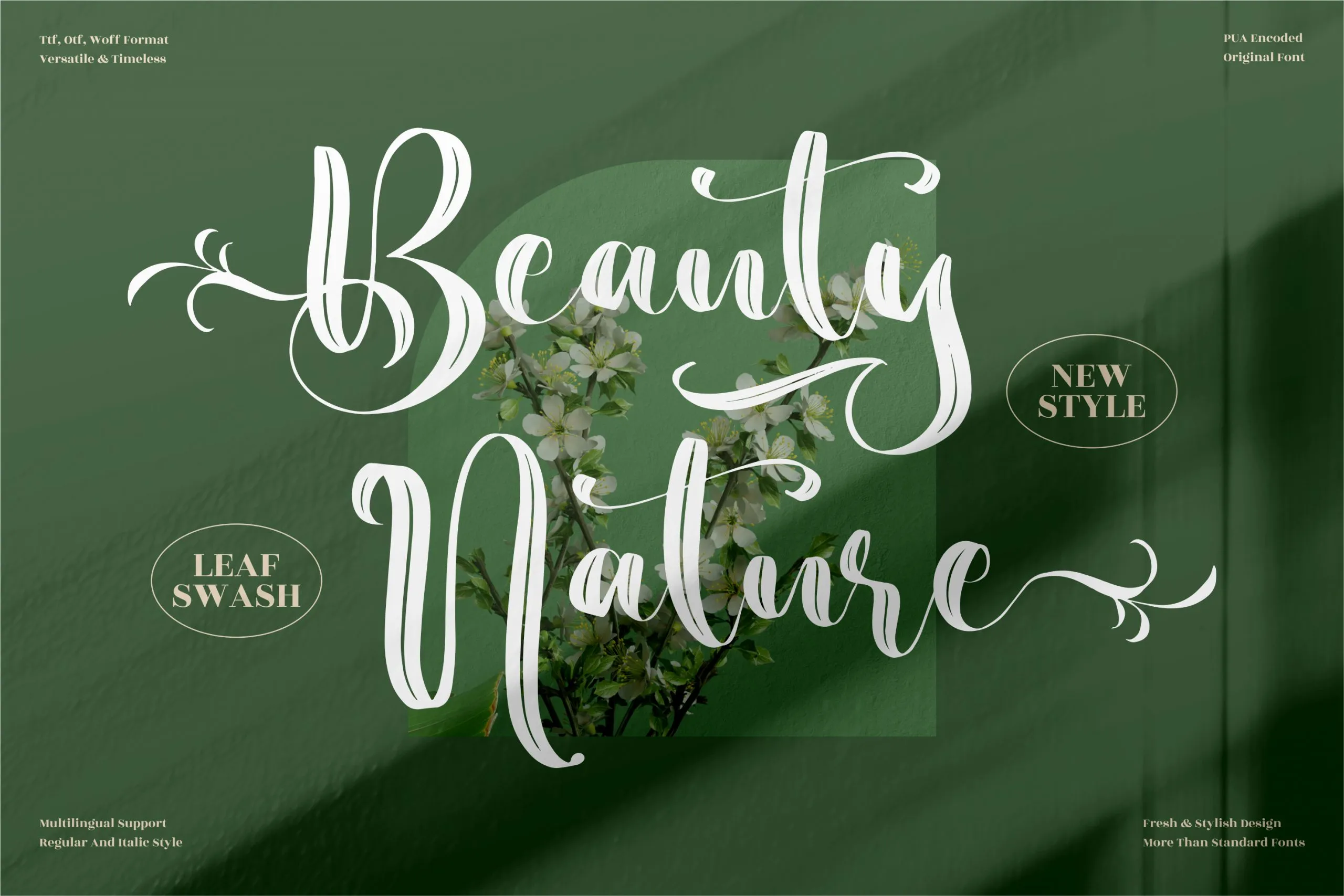
Esta fonte é perfeita para aqueles que buscam uma mistura autêntica e sofisticada. Ideal para criações digitais variadas como logotipos, projetos de marca, designs de móveis de uso doméstico, embalagens de produtos, xícaras personalizadas, cartazes, sacolas de viagem, camisetas, capas de livros, etiquetas e até mesmo para imagens fotográficas. Suas características delicadas e autênticas a tornam uma escolha inteligente para quem deseja dar um toque humano a seus trabalhos. Ainda mais, esta fonte é um excelente adjuvante para eventos especiais e projetos de alto luxo, onde uma mão escrita perfeita pode destacar sua marca ou projeto. Com o ‘Beauty Nature Font’, seus designs ganharão profundidade e sofisticação, tornando-os únicos e imprimindo em seu público um toque pessoal. Este é um recurso font que combina elegância com confidencialidade, trazendo uma qualidade única aos projetos que deseja lançar à luz do dia.